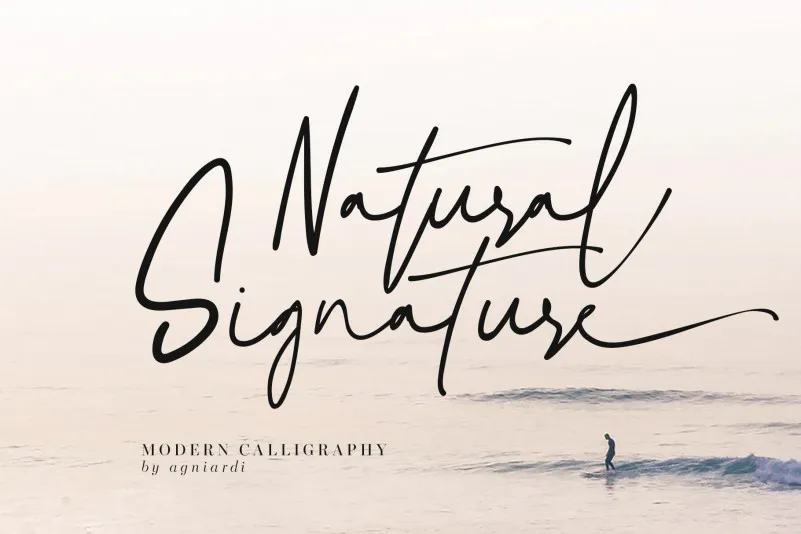
Natural Signature Font – Fonte Grátis
Natural Signature Font
A Natural Signature Font é uma elegante escrita feita à mão que se destaca por sua essência orgânica e encantadora. Suas letras têm um estilo autêntico e um toque descontraído, ideal para adicionar personalidade ao seu design. Imagine a perfeição em cada traço, criando uma conexão única entre o texto e quem lê. Este é o tipo de fonte que você vai amar ter à mão para dar vida aos seus trabalhos, seja ela um cartão de visita sofisticado ou um projeto de design gráfico incrivelmente único. Com a Natural Signature Font, suas criações tornam-se ainda mais únicas e autênticas.
Designer: agniardi